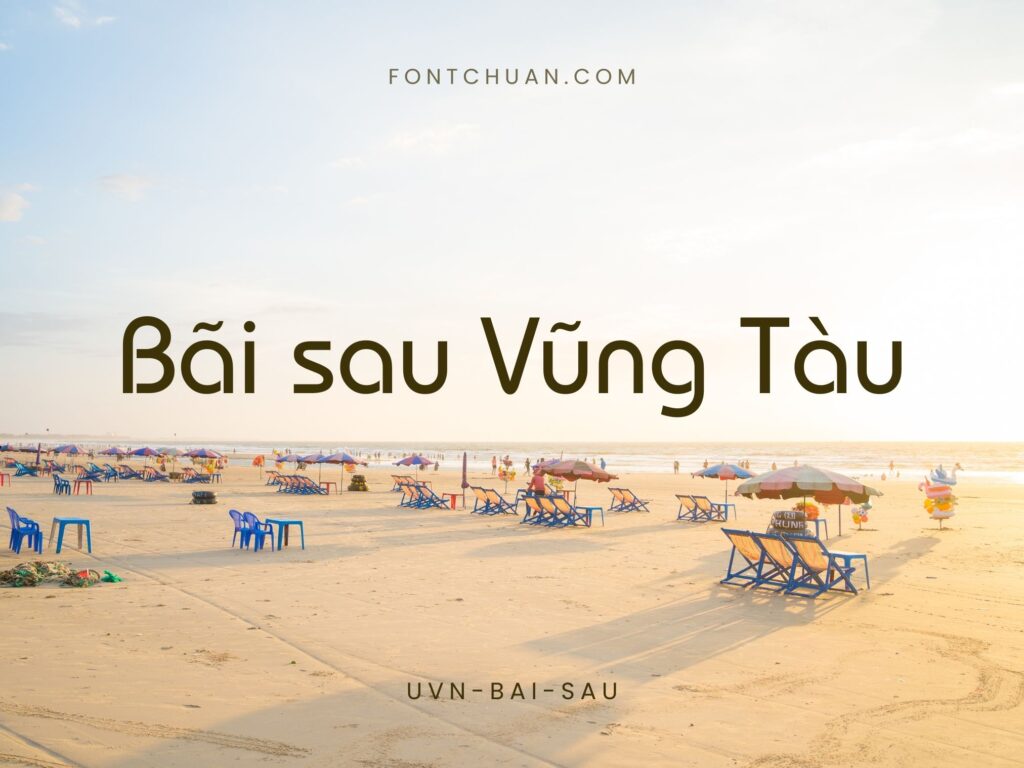
Font UVN Bai Sau Việt Hóa
UVN Bãi Sau là một font chữ mang phong cách hiện đại nhưng vẫn phảng phất nét truyền thống, nằm trong bộ sưu tập font UVN được đông đảo nhà thiết kế Việt Nam yêu thích. Với cảm hứng từ vùng biển Bãi Sau – Vũng Tàu, kiểu chữ này gợi lên hình ảnh phóng khoáng, tự do và có phần hoài niệm. Font này chỉ được sưu tầm và đăng bởi thành viên của Font Chuẩn nhằm chia sẻ đến cộng đồng thiết kế một công cụ hữu ích, được ứng dụng thực tế trong nhiều dự án truyền thông và in ấn.
Thiết kế của UVN Bãi Sau có đặc điểm dễ đọc, đường nét dứt khoát, độ dày đồng đều giúp đảm bảo tính ổn định trong hiển thị. Kiểu chữ này hoạt động tốt trên các tiêu đề, biển hiệu, áp phích hoặc các thiết kế mang tính truyền cảm. Với sắc thái vừa trang trọng vừa gần gũi, font phù hợp với các ngành nghề như quảng cáo, bất động sản, giáo dục và công nghệ. Ngoài ra, nó cũng rất lý tưởng cho các sự kiện như Tết, lễ hội, ngày Nhà giáo hoặc Trung thu.